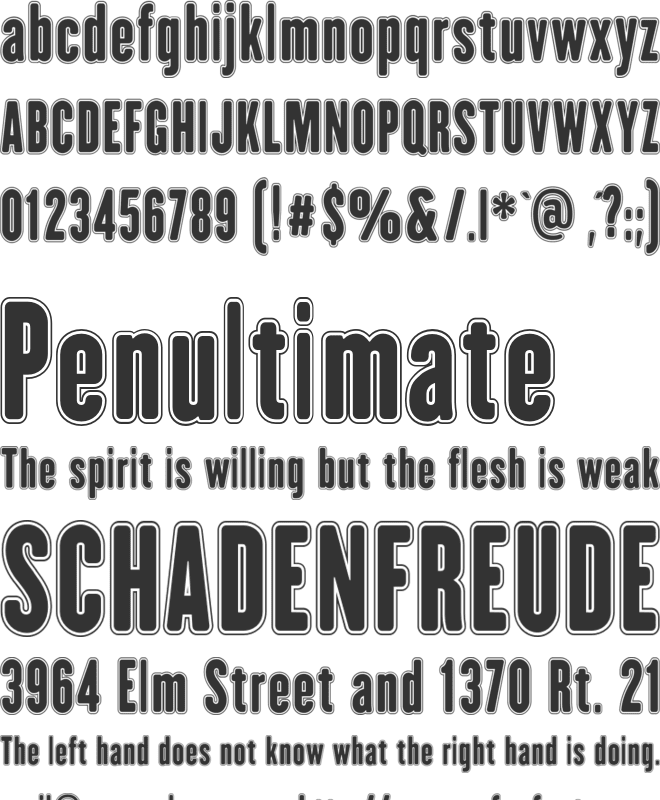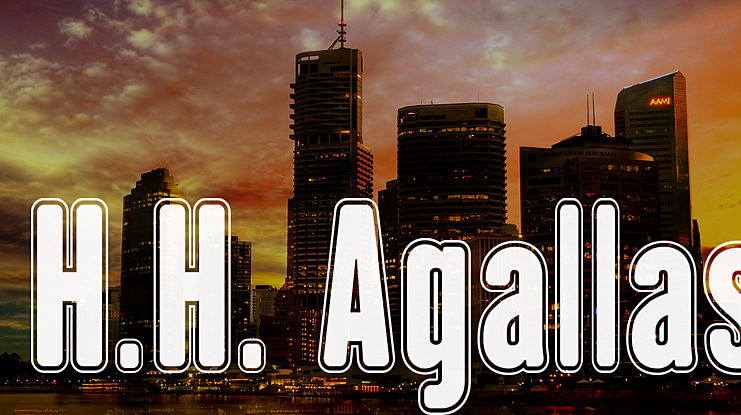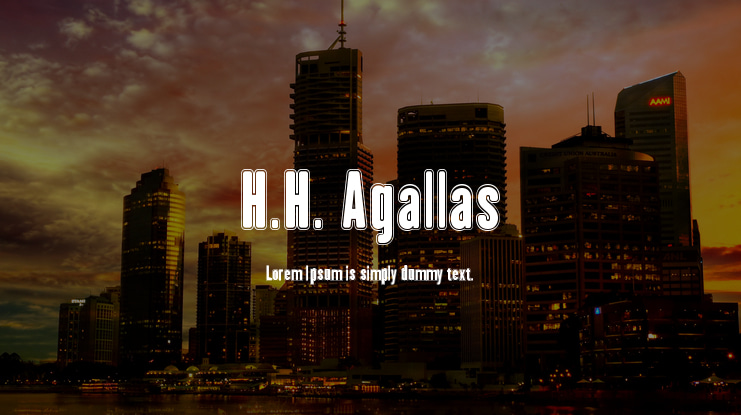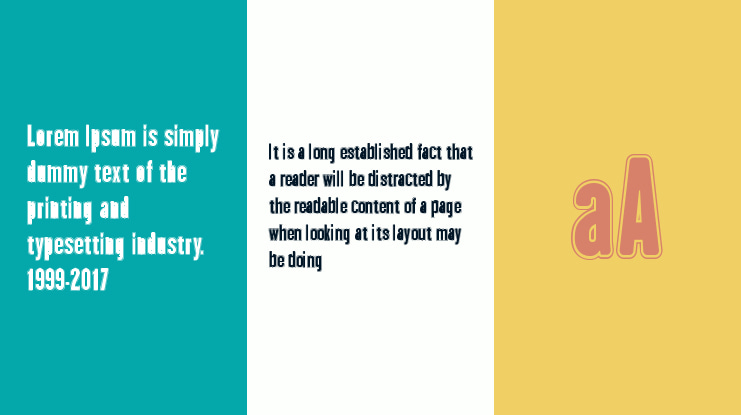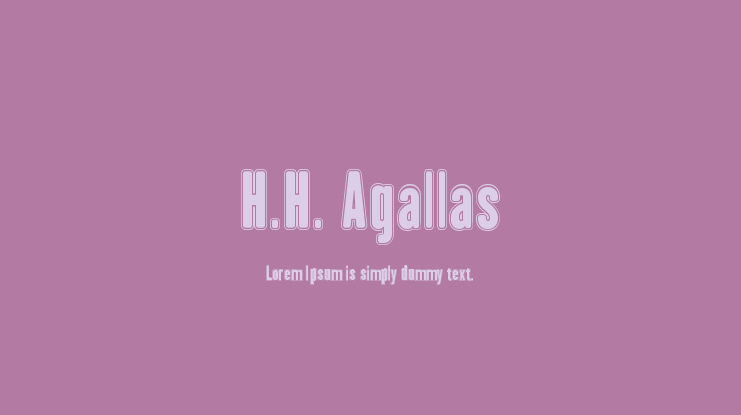
H.H. Agallas Font
H.H. Agallas es una tipografía Heavy, sin serif de estilo universitario, dispone de todos los glifos para todos los lenguajes derivados del latín El nombre está inspirado en el Epagneul Breton de mi sobrino Samuel.